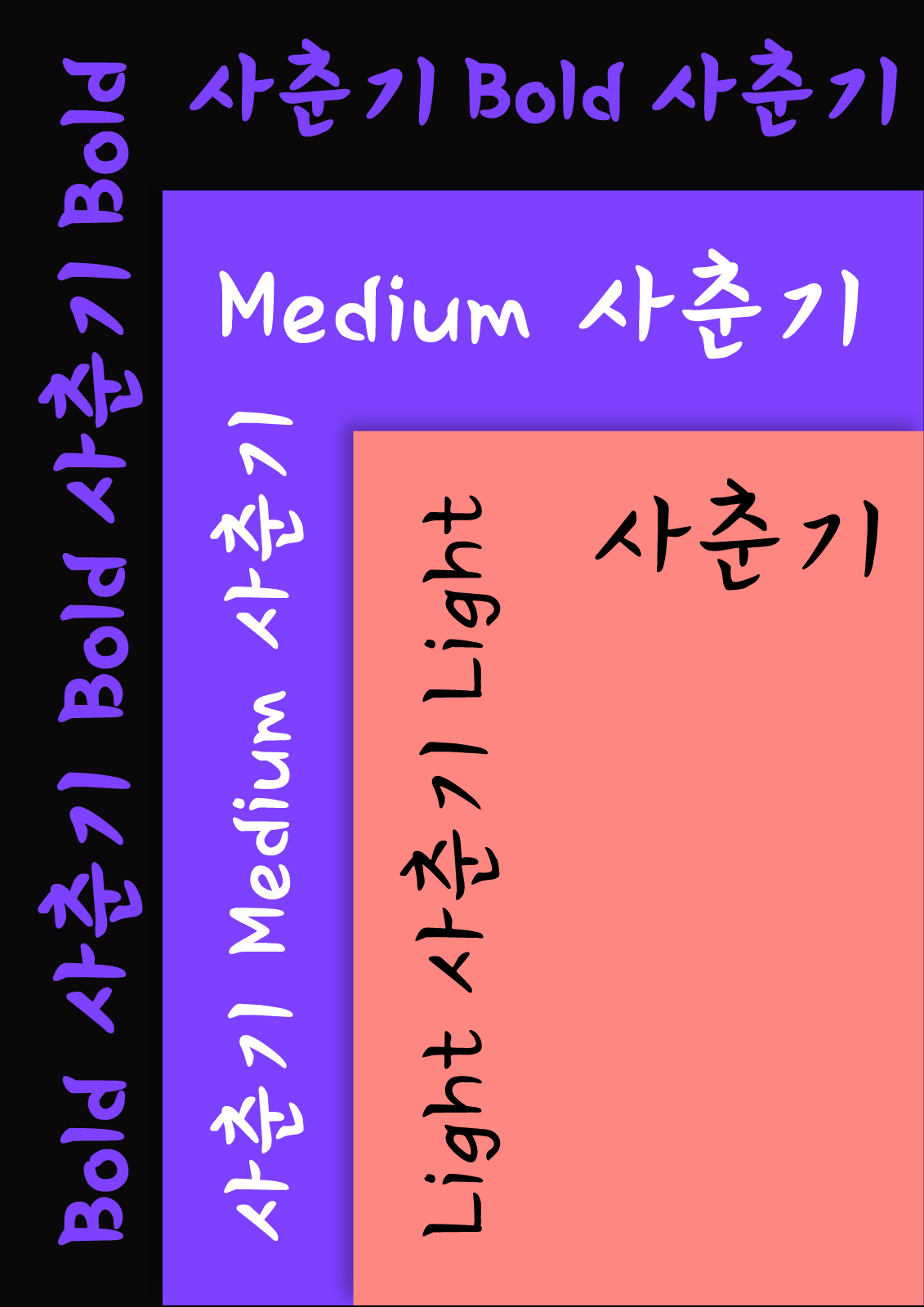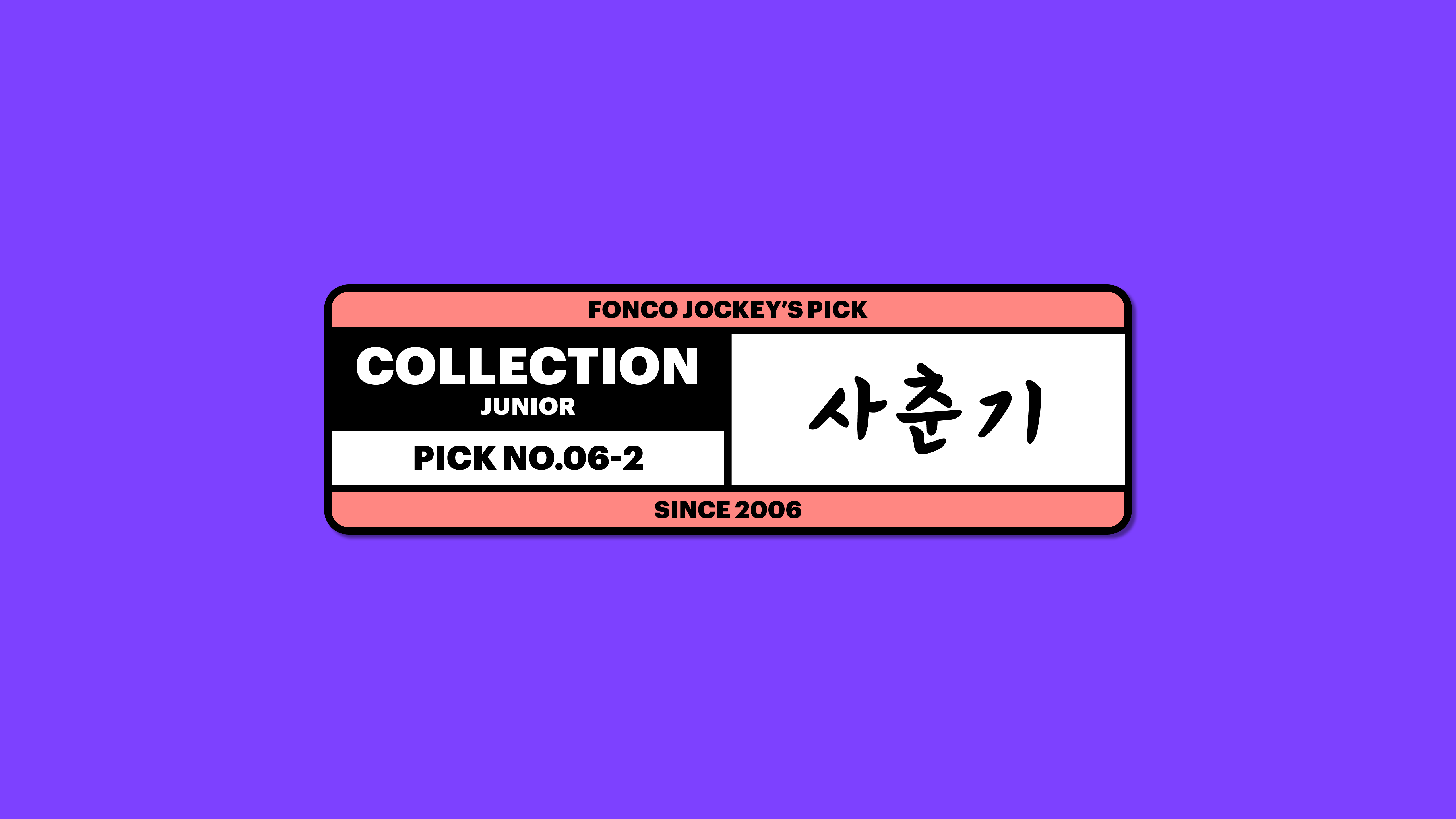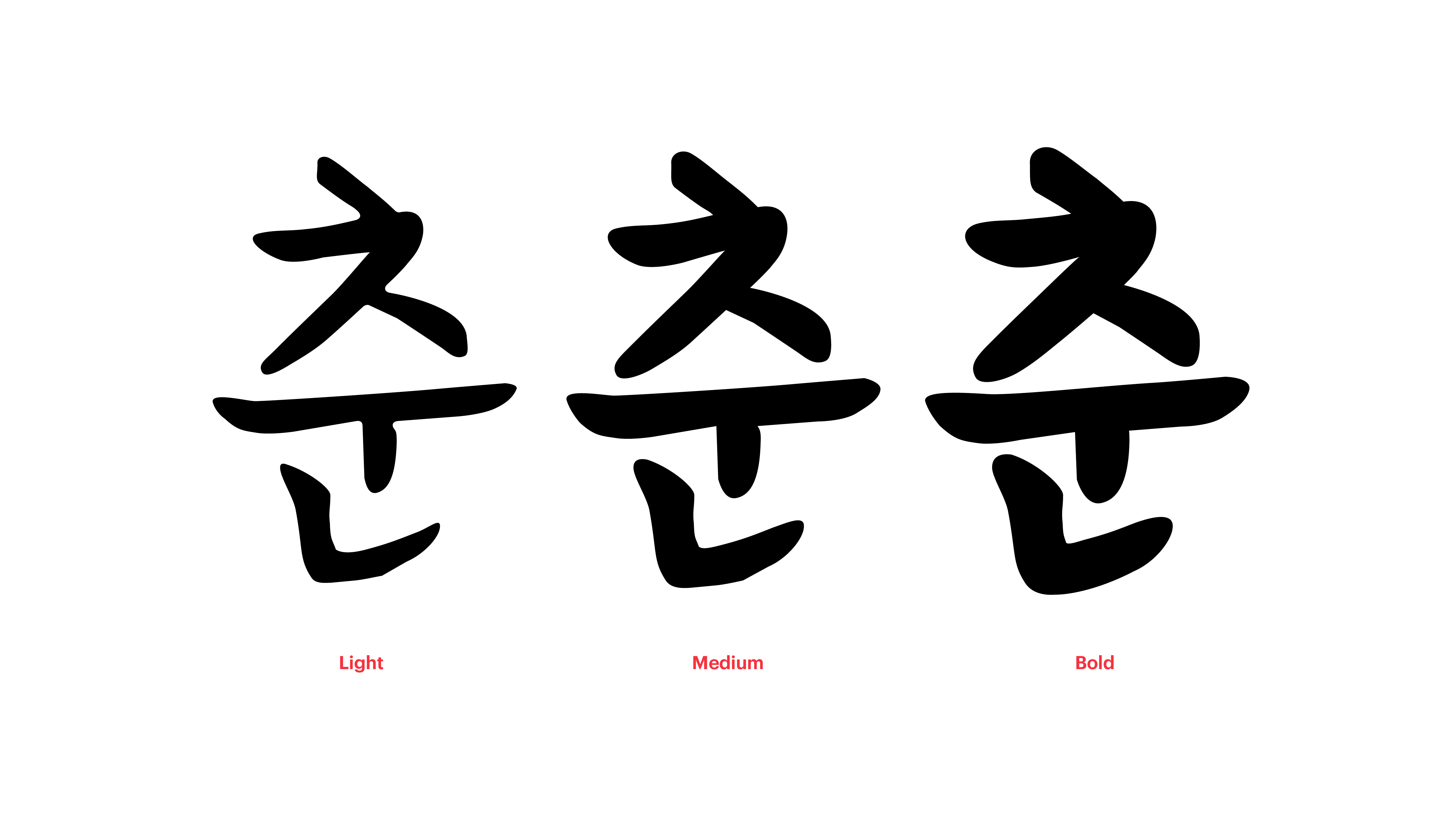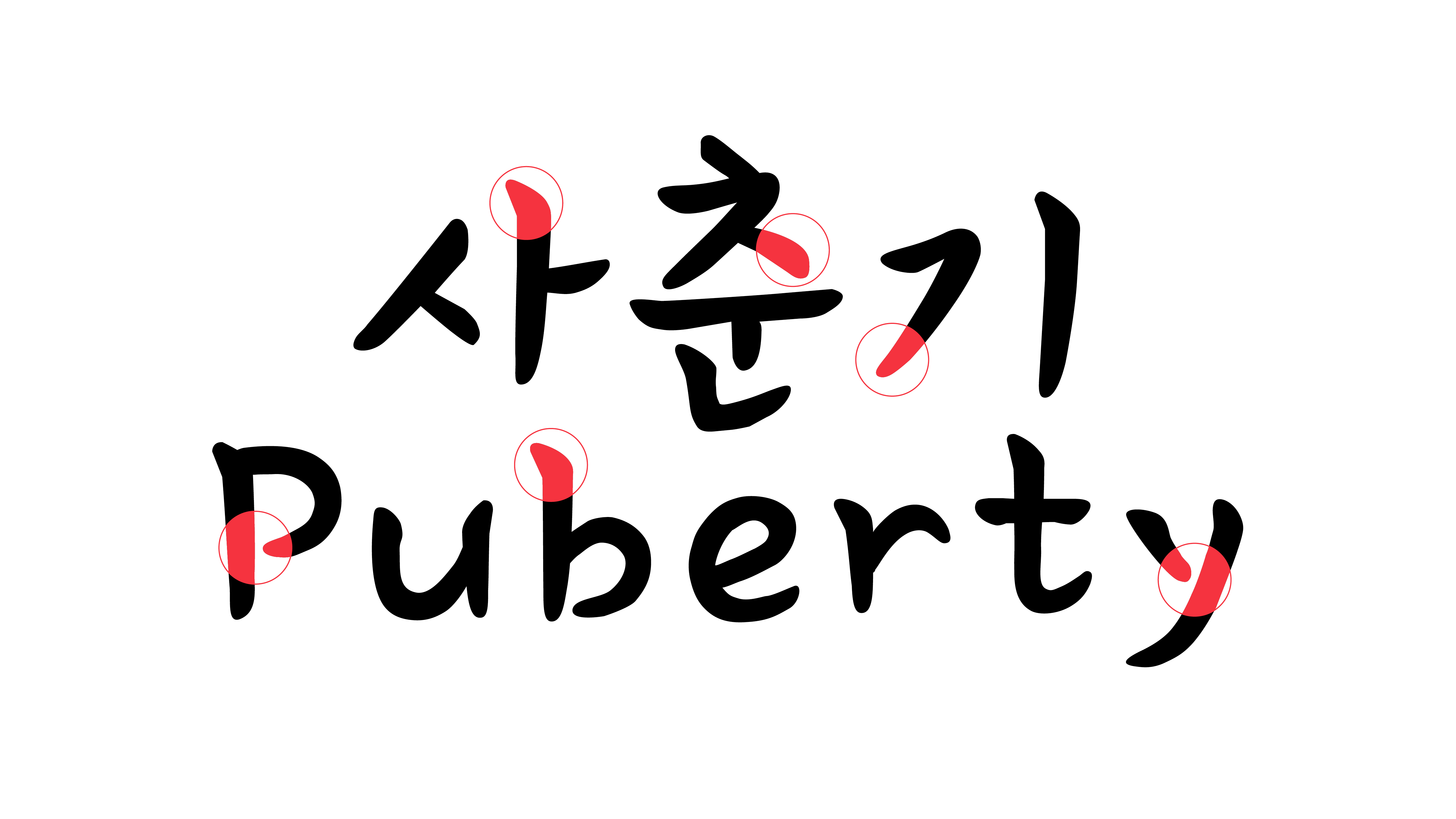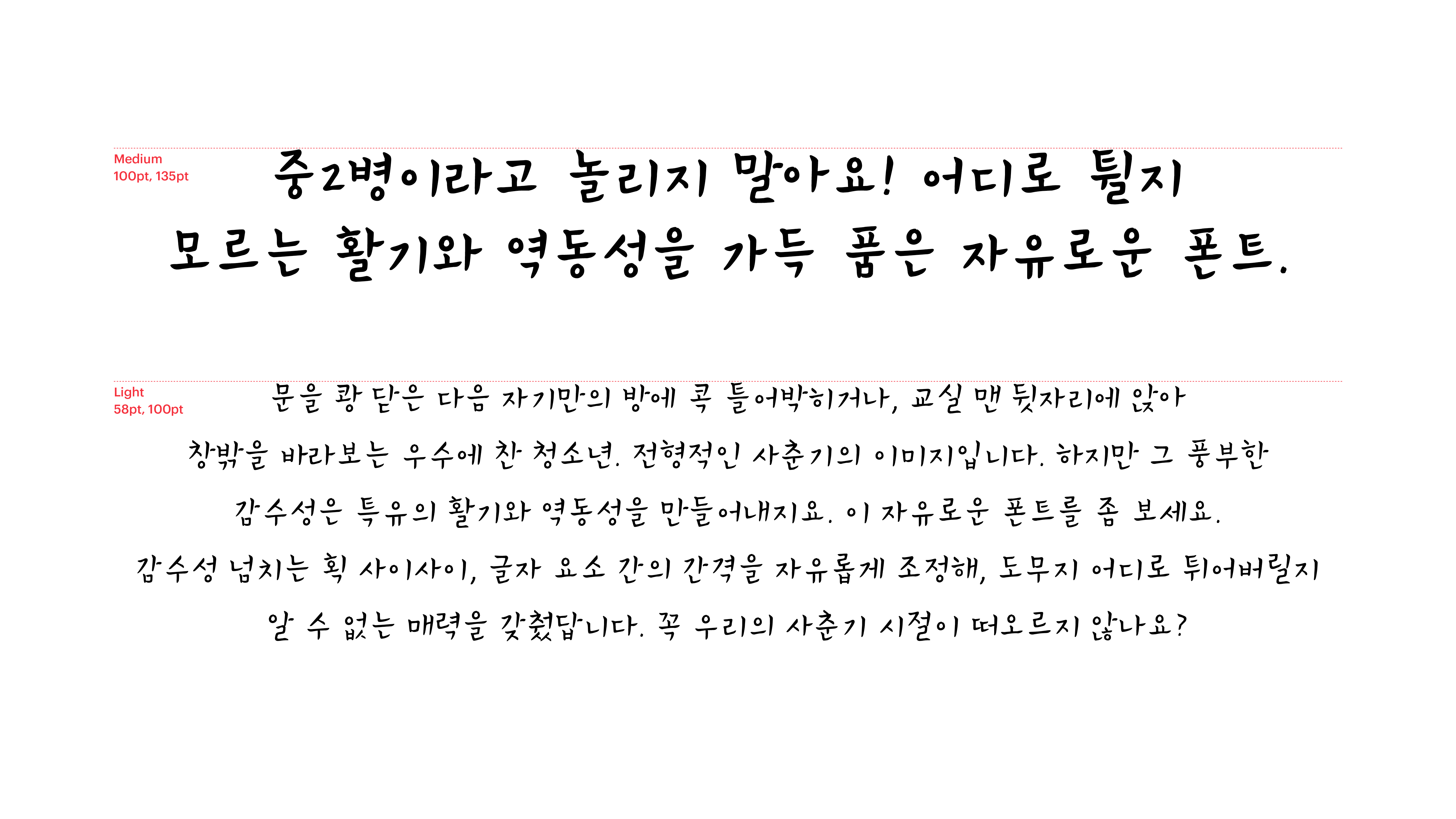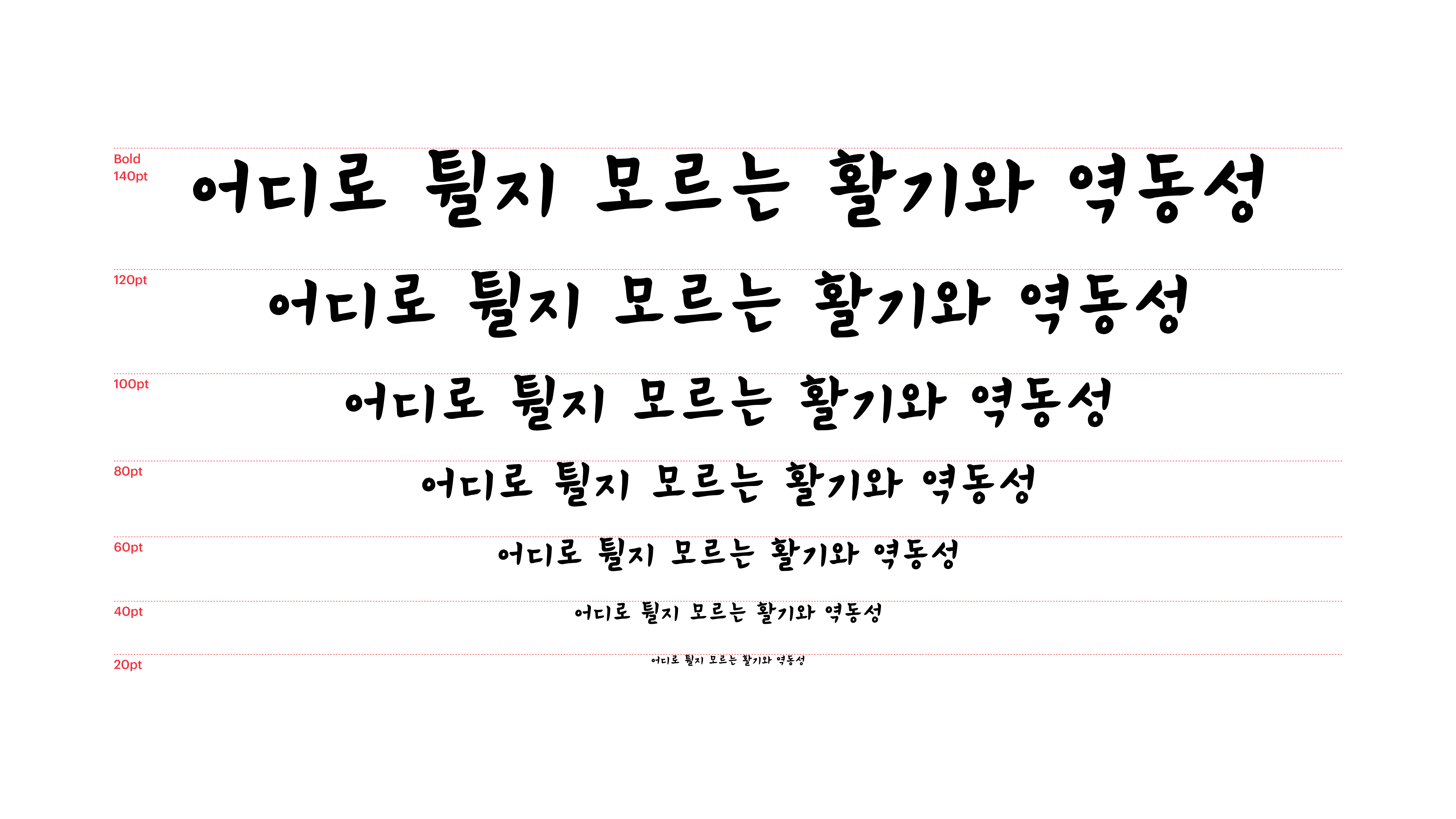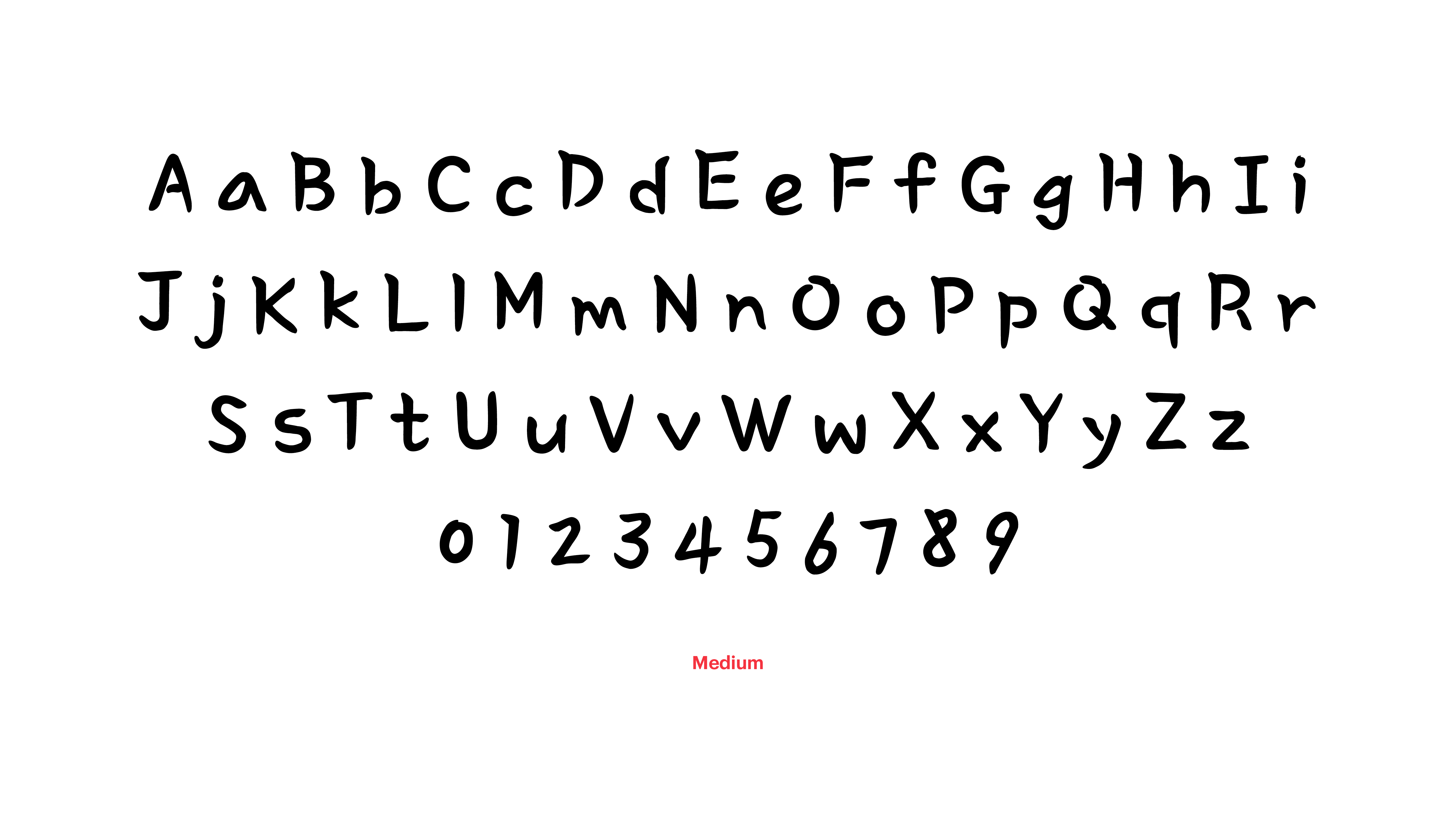
문을 쾅 닫은 다음 자기만의 방에 콕 틀어박히거나, 교실 맨 뒷자리에 앉아 창밖을 바라보는 우수에 찬 청소년. 전형적인 사춘기의 이미지입니다. 하지만 그 풍부한 감수성은 특유의 활기와 역동성을 만들어내지요. 이 자유로운 폰트를 좀 보세요. 감수성 넘치는 획 사이사이, 글자 요소 간의 간격을 자유롭게 조정해, 도무지 어디로 튀어버릴지 알 수 없는 매력을 갖췄답니다. 꼭 우리의 사춘기 시절이 떠오르지 않나요?
Yoon 사춘기